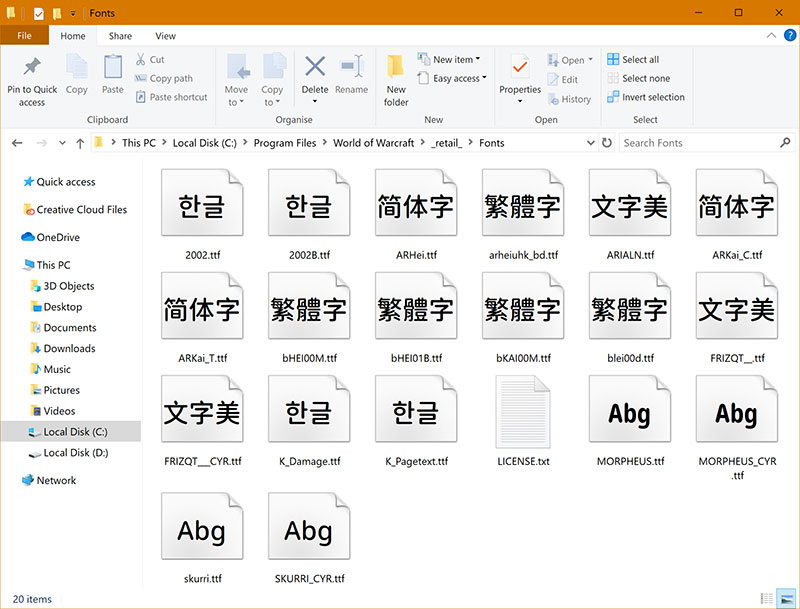
有爱圆体(Nowar Rounded),是《魔兽世界》和《魔兽世界:经典怀旧服》字体包。是由Noto Rounded和资源圆体的合并而来的字体,有爱圆体也从思源黑体的修改而来,所以,在中文字形上有爱圆体和资源圆体差不多。但是有爱圆体只有有四个字重,分别是Light,Regular,Medium,Bold,要比资源圆体少些字重。